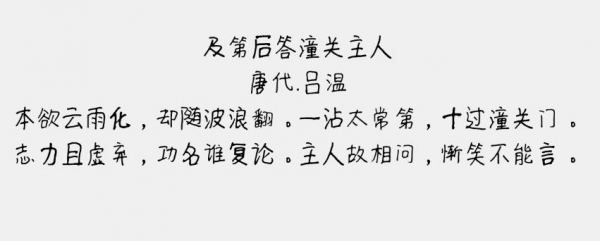
紅豆遇見美好是一款非常不錯(cuò)的手寫字體,個(gè)性醒目,具有強(qiáng)烈的視覺沖擊力,適應(yīng)于報(bào)紙和雜志和書籍中常用字體, 海報(bào)、個(gè)性促進(jìn)品牌標(biāo)志設(shè)計(jì)、字體設(shè)計(jì)、等環(huán)境使用。歡迎喜歡這款字體的朋友下載收藏。